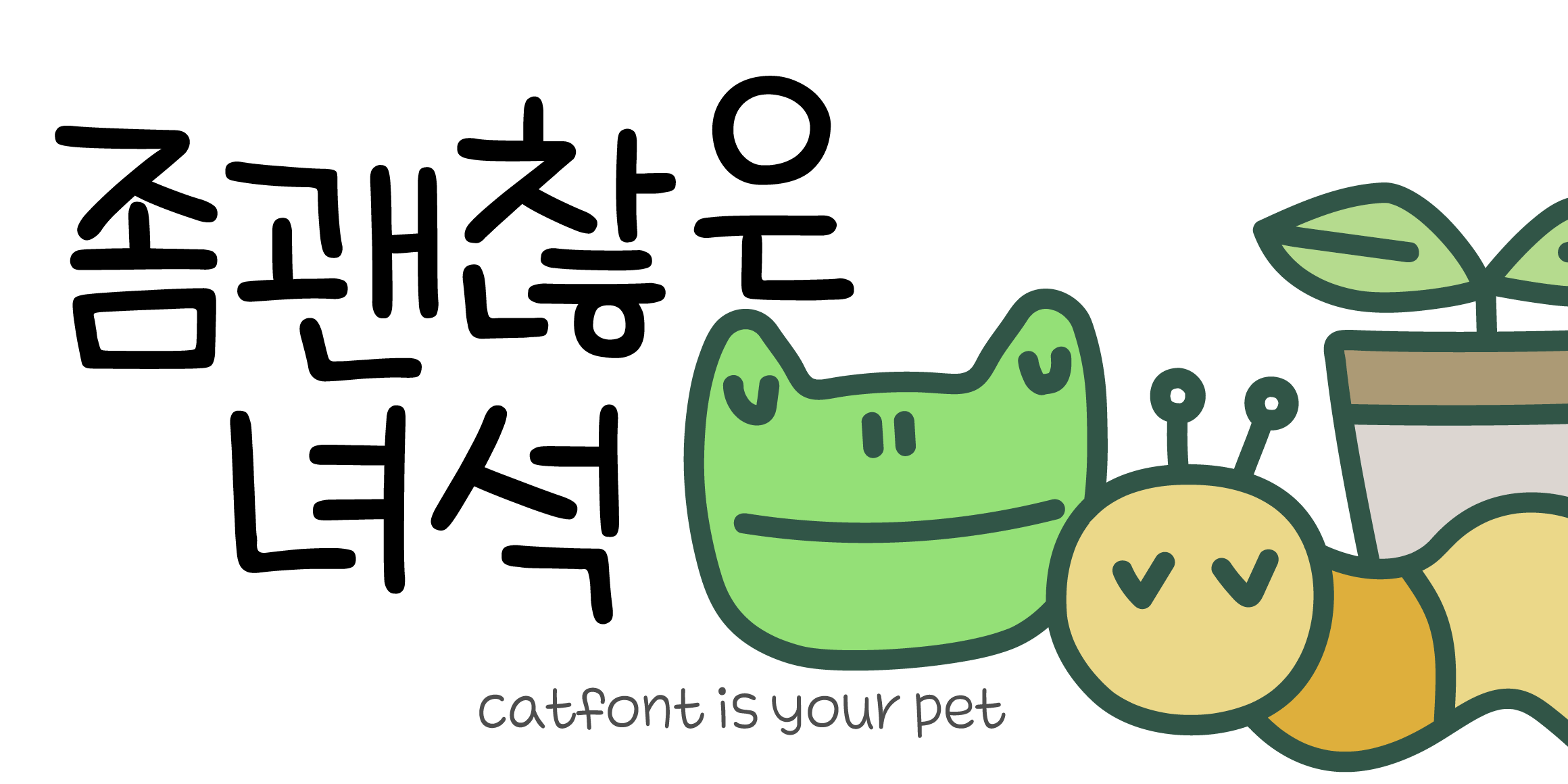
러블리한 체크무늬를 닮은
시그니처 글꼴입니다.
♥키보드 ; > ; ) : ! : : ? : 을 연달아 치면
매력적인 캣딩벳이 나타납니다.
♥영어 일어 베트남어를 포함한
독일 프랑스 러시아 이탈리아 포르투갈 스페인 터키 등
유럽의 다양한 국가들의 언어도 함께 지원하는 등
폭넓은 언어와 특수문자 지원을 합니다.
♥캣폰트의 디자인은 오랜 시간 연구한 결과물입니다.